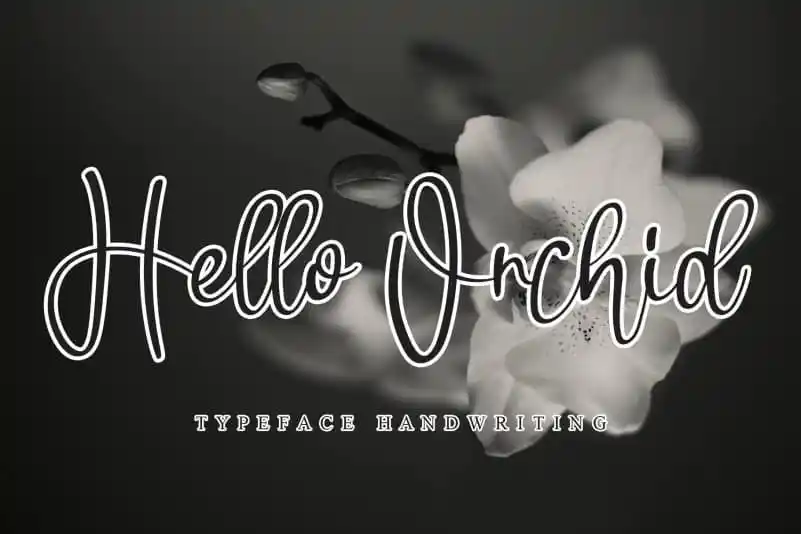
Hello Orchid Handwritten Font
A fonte ‘Hello Orchid Handwritten Font’ é uma elegante escrita a mão delicada. Suas letras distintas e bem redondas criam um estilo único, tornando-a verdadeira obra de arte. Perfeita para quem valoriza tanto a personalidade quanto a sofisticação na sua designação visual, esta fonte oferece inúmeras possibilidades criativas. Ela é perfeita para adicionar uma pitada de elegância ao seu trabalho gráfico. Use-a para criar designs impressionantes que expressam sua identidade única.